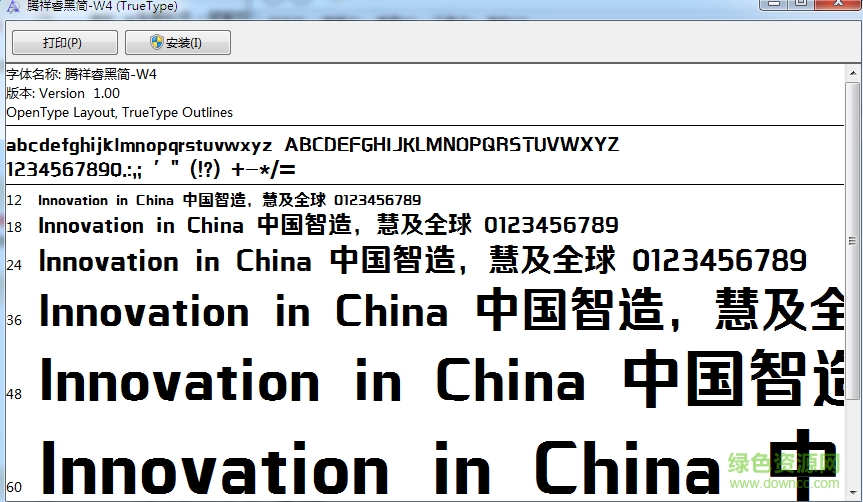
騰祥睿黑簡 w4
騰祥睿黑簡W4為大黑一款,整體筆畫看起來粗壯、清晰、易于閱讀,筆型嚴謹規(guī)范,有喜歡的朋友歡迎來綠色資源網(wǎng)下載,讓你的電腦上也有這款漂亮的字體!
字體簡介
騰祥睿黑簡W4賦予了黑體全新的設計理念,點形到撇、捺形都做了大膽的創(chuàng)新。塔形頓點、撇點和部分折筆處外圓角的設計,使得字形看上去內(nèi)斂、圓潤、弱化了黑體尖銳和張揚的感覺,適用于標題、小標題、大標題等。
騰祥睿黑簡W4